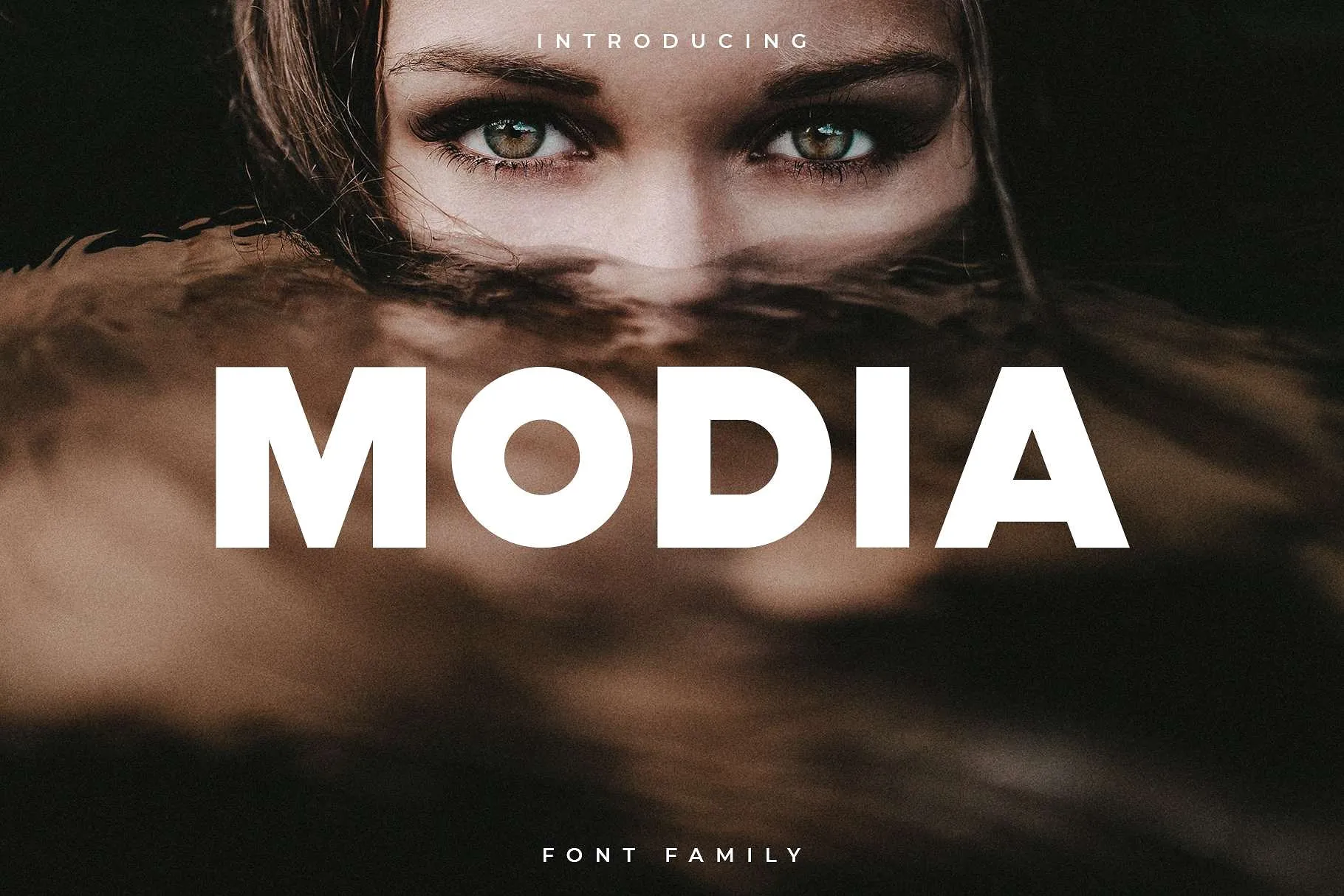
Modia Font Family – Download Grátis
Modia Font Family é uma nova família de tipografia sans-serif moderna que traz à luz um estilo robusto e limpo. Esta fonte está ideal para projetos com alto impacto visual, especialmente aquelas necessitando de um toque de seriedade clássica. Suas linhas finas e diretas conferem uma aparência sólida a qualquer projeto gráfico. Modia é perfeita tanto para logos poderosos quanto para websites, embalagens de produtos, materiais de mídia impressa e mesmo designs de roupas. Com o seu design versátil, a fonte se adaptará facilmente em diversas aplicações gráficas. Uma das marcas mais belas e criativas que você pode encontrar em sua categoria. Seja para ilustrar um novo site ou criar uma identidade visual memorável, Modia é uma escolha ideal.